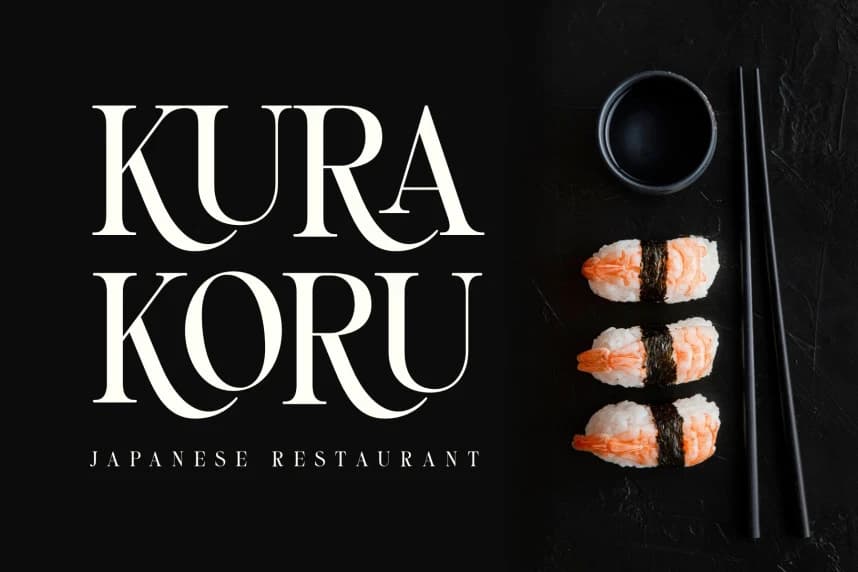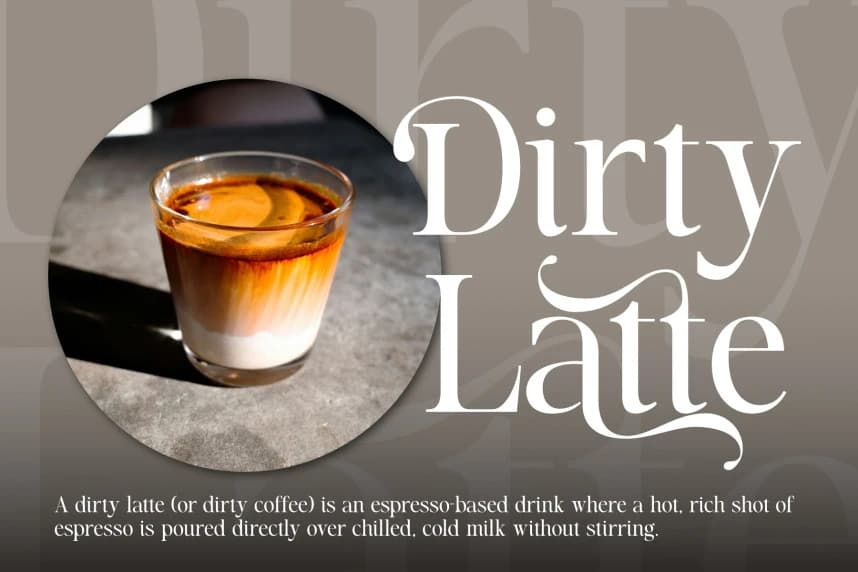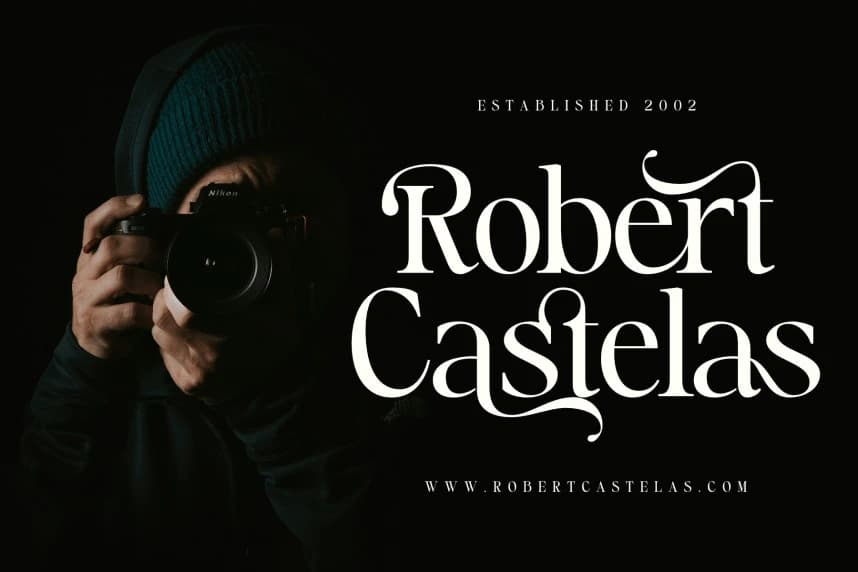
Astrel Madesly Yazı Tipi
Astrel Madesly Font, zarafeti modern estetik çekicilikle birleştiren sanatsal bir display serif yazı tipidir; özenle işlenmiş ligatürler ve şık alternatifler sunar ve zahmetsizce lüks ve ifade gücü yüksek bir tipografi yaratmak için tasarlanmıştır.
Astrel Madesly Yazı Tipi, zarafeti modern estetik cazibesiyle birleştiren sanatsal bir gösterişli serif fontudur; özenle tasarlanmış ligatürler ve zarif alternatifler içerir, lüks ve ifadeli tipografiyi zahmetsizce yaratmak için tasarlanmıştır.